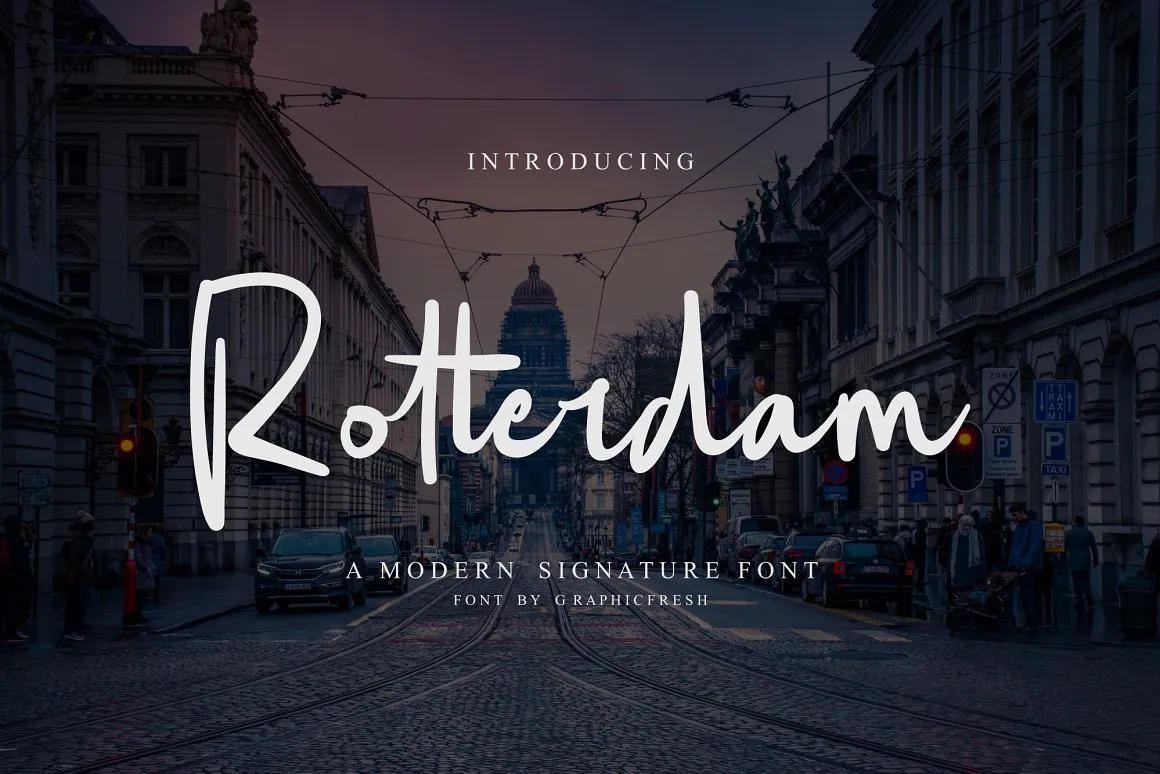
Rotterdam Script Font – Fonte Grátis
Rotterdam Script Font
Descubra Rotterdam Script Font, uma elegante e sofisticada fonte que enriquece seu design com sua linhagem suave e curvilínea. Inspirado no estiloso desenho de cidades como Rotterdam, esse roteiro gráfico oferece um conjunto de letras perfeito para projetos variados. Seja para criação de logotipos ou cartões de visita, layouts de revistas, convites de eventos, cabeçalhos criativos ou até mesmo obras publicitárias de grande escala. Com sua forma atraente e sofisticada, Rotterdam Script é uma fonte de texto que se destaca, especialmente quando usada em projetos visuais. Suas curvas perfeitas e arredondamentos suaves fazem com que Rotterdam seja um recurso gráfico indispensável para designers amadores e profissionais. Sua beleza natural e sua elegância tornam a Rotterdam Script uma escolha ótima para qualquer projeto gráfico.